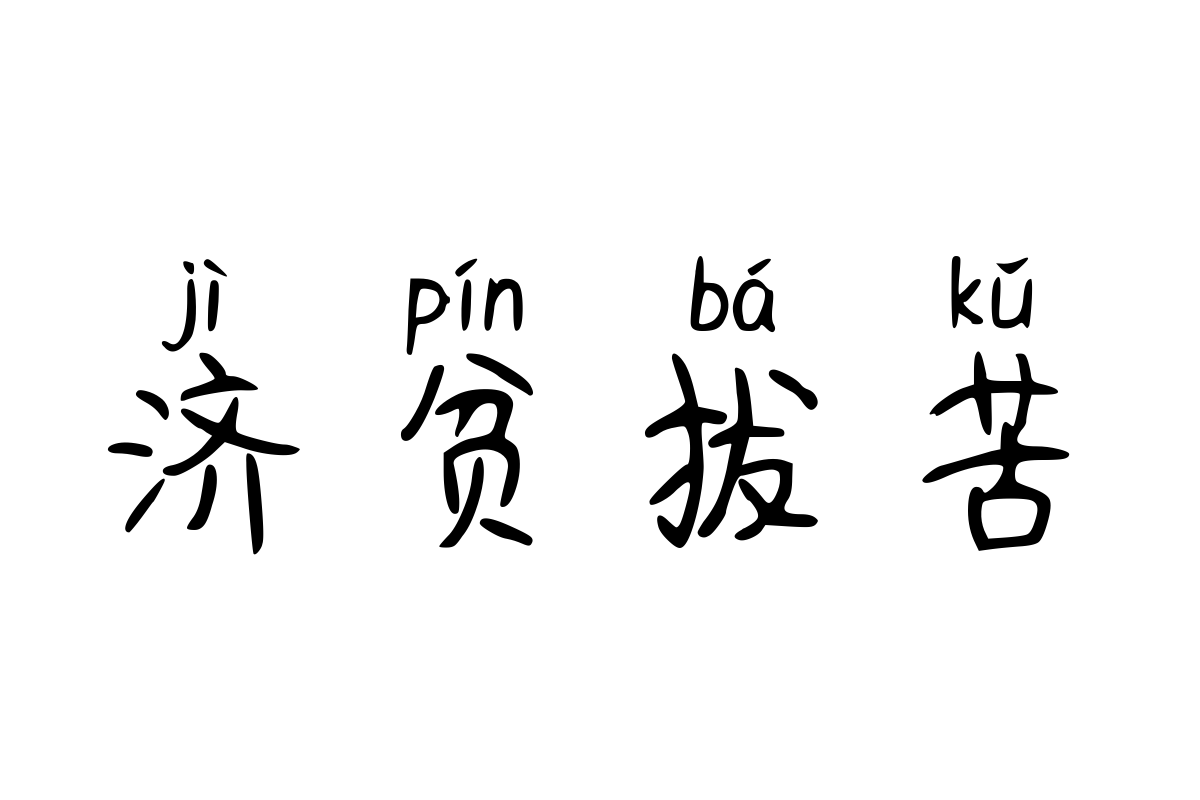
思雨小萌猫是一款非常可爱的字体,其特点如下:
1. 字体风格:思雨小萌猫字体采用了卡通化的设计,线条流畅,形象可爱,给人一种轻松愉快的感觉。
2. 字形特点:这款字体的字形圆润饱满,笔画粗细适中,易于阅读和书写。同时,字体结构紧凑,整体协调,给人一种和谐美感。
3. 应用场景:思雨小萌猫字体适用于各种需要可爱风格的设计作品,如儿童插画、卡通海报、游戏界面等。它能够为作品增添一份童趣和活力。
总之,思雨小萌猫字体是一款非常适合用于可爱风格设计的字体,它的可爱风格和易读性使其在各种设计作品中都能发挥出独特的魅力。